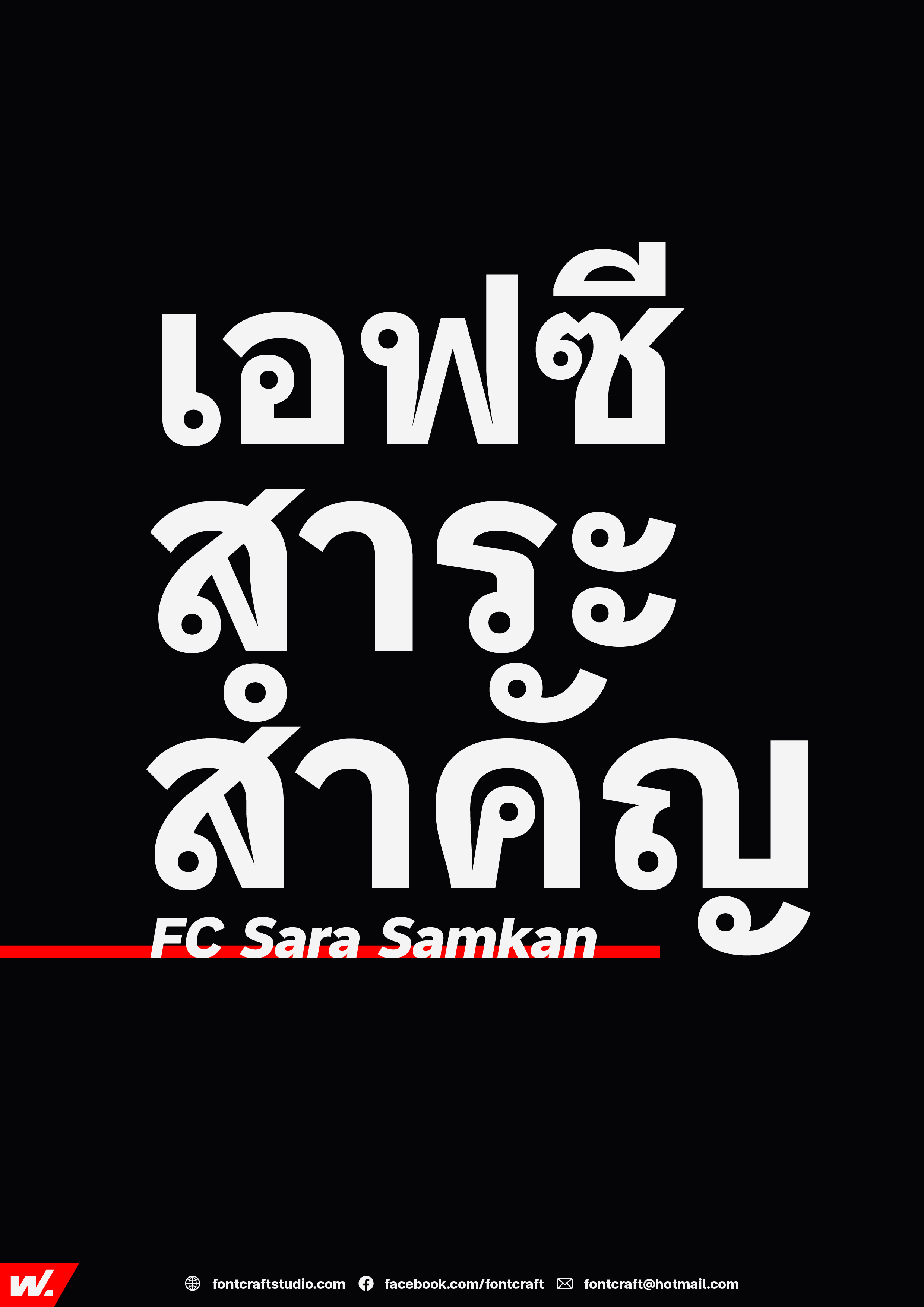
ฟอนต์เอฟซี สาระสำคัญ (FC Sara Samkan)
ฟอนต์แบบมีหัวกลมตัวอ่าน ใช้งานตัวใหญ่ก็ปัง ตัวเล็กเนื้อความก็รอดครับ
ฟอนต์เอฟซี สาระสำคัญ (FC Sara Samkan)
กล่าวเรื่องสำคัญ ฟอนต์ต้องดูเด่น อ่านเห็นชัดเจน
แบบอักษรฐานตรงทรงทางการ ใช้ขนาดใหญ่ตัวหนาดูโดดเด่น เน้นย้ำความชัดเจนในเจตนา ใช้ขนาดเล็กตัวบางอ่านได้ง่าย เป็นระเบียบและเรียบร้อย
ชุดฟอนต์ประกอบด้วย 9 ระดับน้ำหนัก พร้อมตัวเอนรวม 18 สไตล์ มี Variable Font แยกจากชุดปกติ